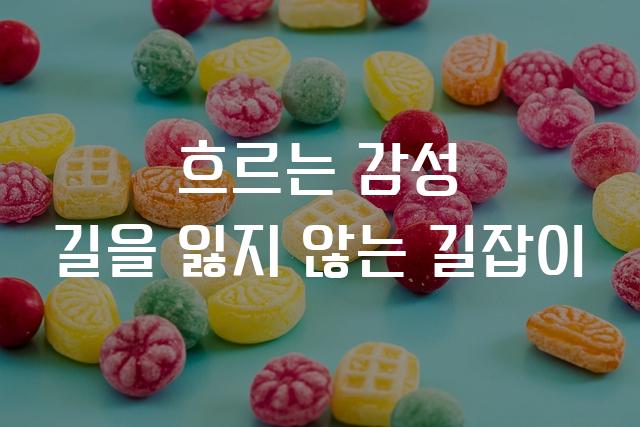
예스 고딕은 예스24에서 제작한 기본적인 고딕 폰트로, 문서 작성에 최적화되어 있습니다. 깔끔하고 명료한 느낌을 주며, 각 글자의 선명도가 높아 읽기 쉽습니다.
예스 고딕은(는)
기본 고딕, 감성적인, 부드러움 계열의 생김새를 가지고 있으며
웹/앱 디자인, 보고서/문서, 출판물 제목 등에서 자주 활용되며, 효과적인 메시지 전달에 적합합니다.
이 폰트는 크리에이티브, 기술/IT, 금융/비즈니스 분야에 잘 어울리며,
명확한, 전문적인, 단순한 느낌을 담고 있는 것이 특징입니다.
이 폰트와 유사한 폰트로는 나눔고딕, 맑은 고딕, 한나체 등이 있어요. 함께 비교해 보시면 좋습니다!